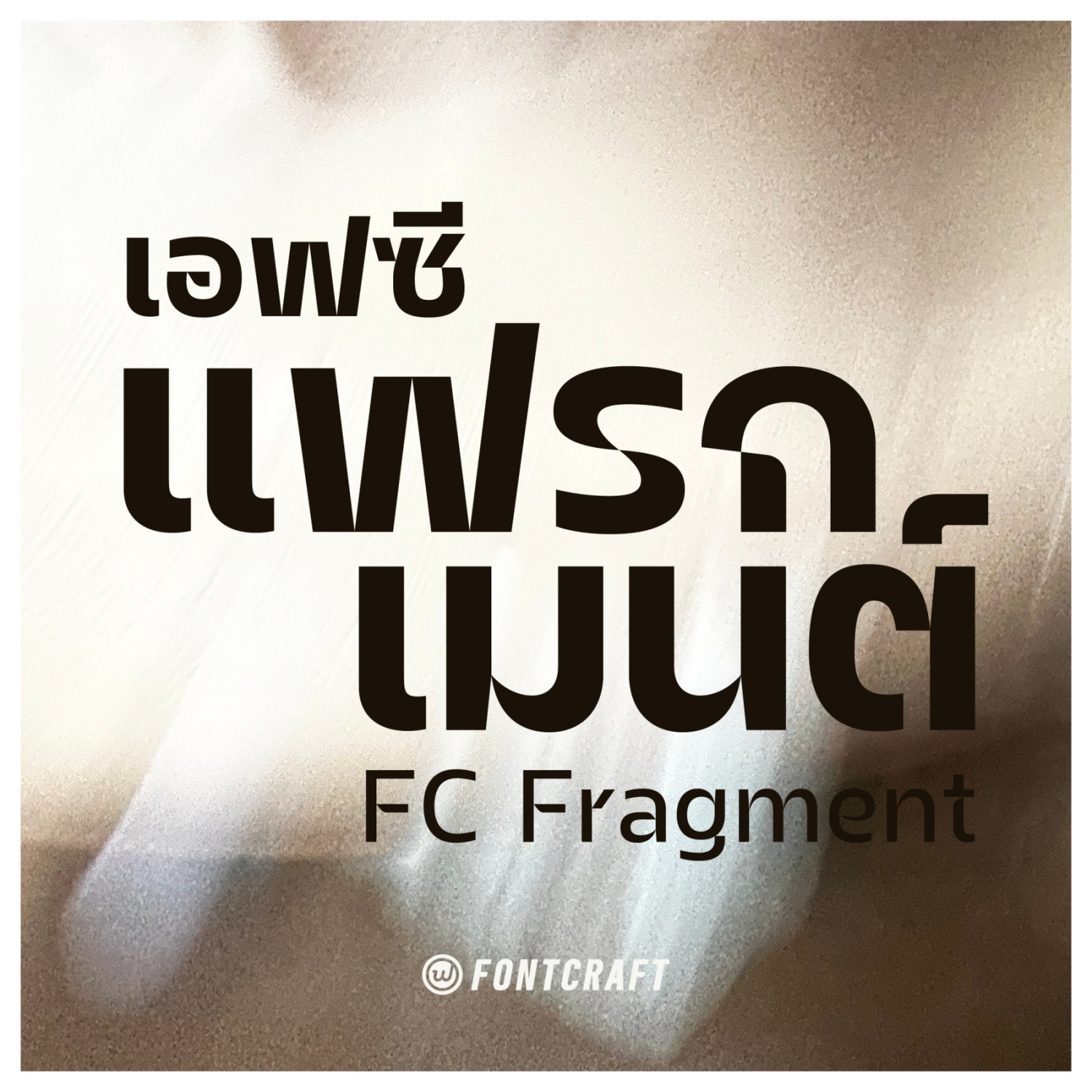
เอฟซี แฟรกเมนต์ (FC Fragment)
ฟอนต์เอฟซี แฟรกเมนต์ (FC Fragment)
"ชิ้นส่วน" คือโจทย์ของการออกแบบ ที่ต้องการให้แต่ละตัวอักษรประกอบกันด้วยชิ้นส่วนมากกว่าหนึ่งชิ้น
โดยที่แต่ละชิ้นไม่ติดกันแต่บรรจบกันอย่างแผ่วเบาและลงตัว
เหมาะสำหรับการใช้งานพาดหัวที่ต้องการความแตกต่าง ท้าทายขนบเดิมในการออกแบบ และยังคงอ่านได้ที่น้ำหนักตัวบางลง
ฟอนต์เอฟซี แฟรกเมนต์ (FC Fragment)
ฟอนต์คอนเซ็ปต์ชัดๆ แก้ปรับกลับไปมาระหว่างน้ำหนักอยู่หลายรอบ